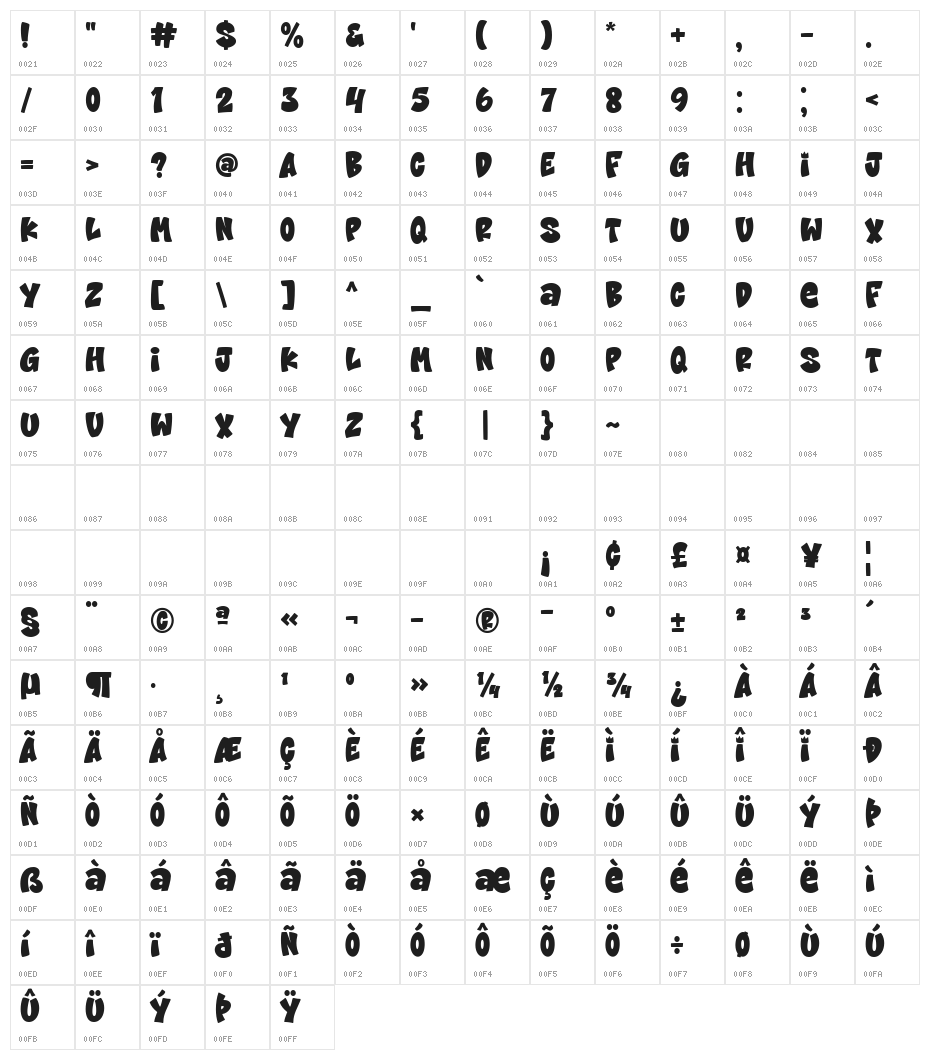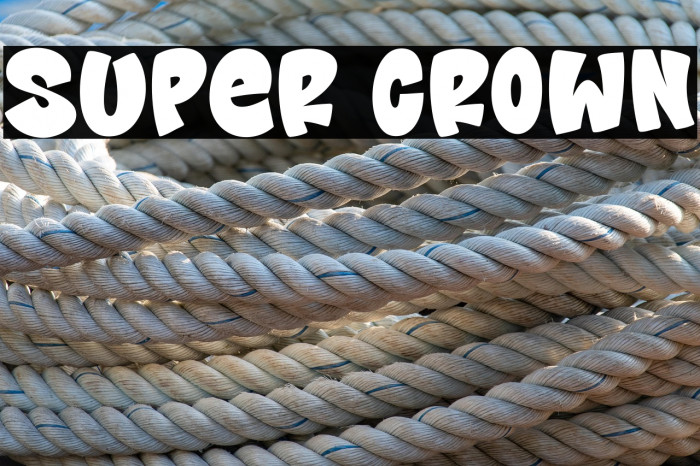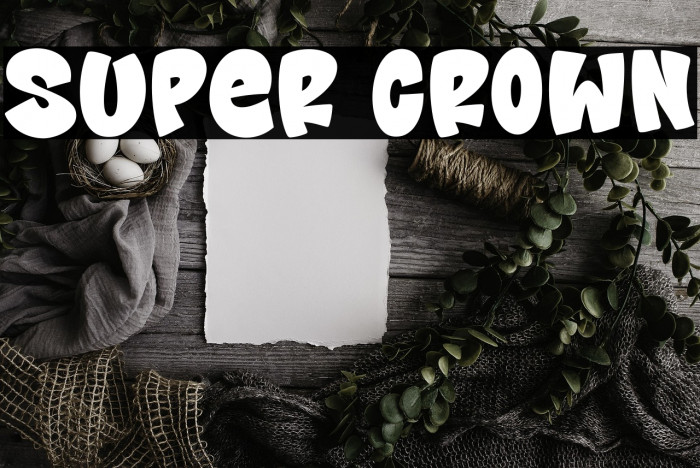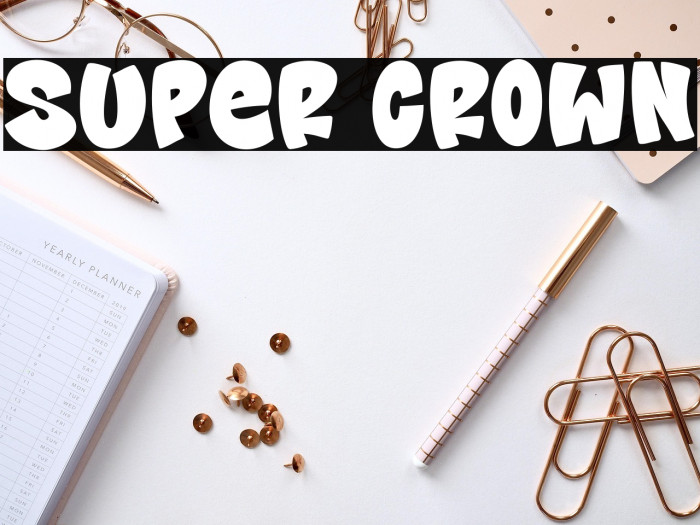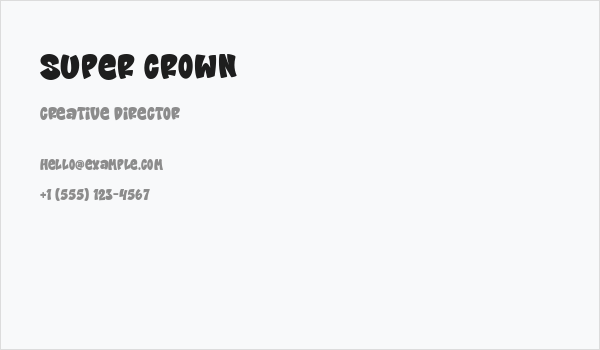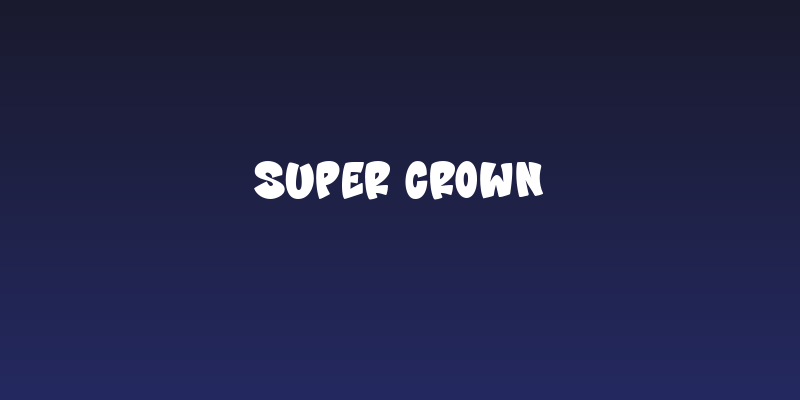
Super Crown Font
| Stile generale | Playful, Whimsical |
| Progetti proposti | Ideal for children's books, playful branding, comic strips, and creative posters. |